A seriedade e a simpatia do Grupo Boticário, em cada assinatura
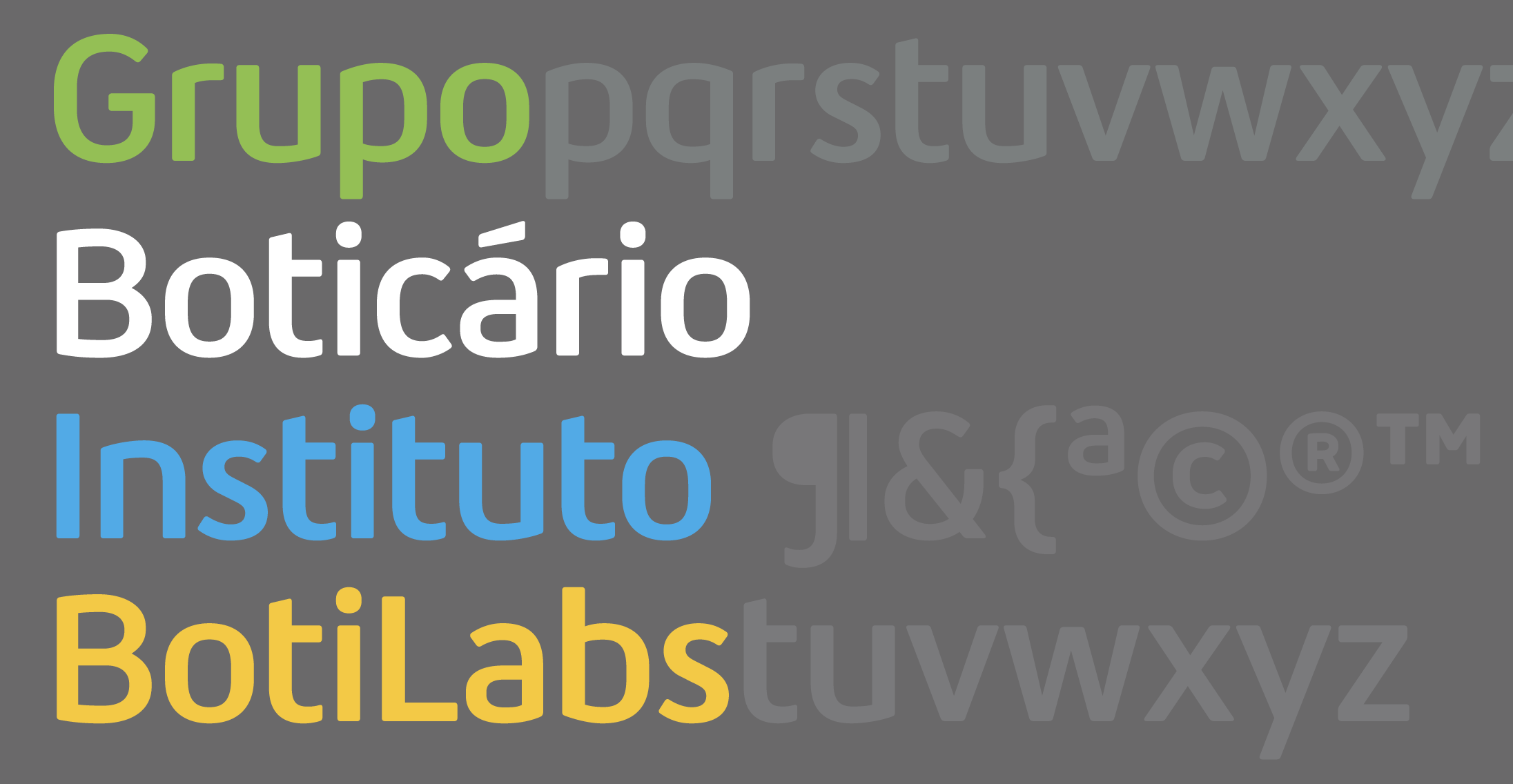
O Grupo Boticário aumentou sua atuação em diversos segmentos de mercado, de beleza ao setor financeiro. Transmitir os atributos como solidez e robustez, sem perder o lado humano e belo, foi o desafio recebido pela FutureBrand.
Em conjunto com a Fabio Haag Type, uma tipografia sob medida foi criada para a marca corporativa e de iniciativas, como Fundação Grupo Boticário e Instituto Grupo Boticário. O desenho das letras possui uma rigorosa serenidade que é balanceada com a leveza dos cantos arredondados.
O resultado é uma tipografia extremamente profissional, exaltando a credibilidade do Grupo Boticário, mas sempre simpática, com um sorriso no rosto.
“Ao desenvolver o universo visual do Grupo Boticário criamos, junto dele, uma tipografia bela e imponente que marca a sua continuidade. De certo modo, estamos traduzindo visualmente a evolução do mercado de beleza no Brasil.” – Karen Fontana, Líder Criativa, FutureBrand São Paulo